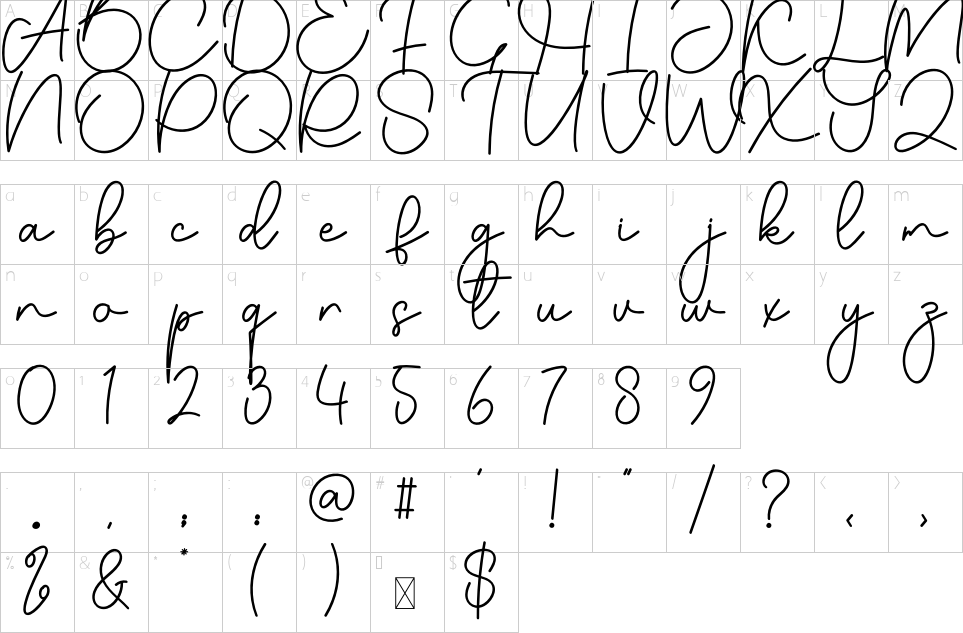
Adelya é uma fonte elegante e moderna, ideal para projetos que exigem sofisticação e simplicidade. Desenvolvida por scratchones, essa fonte foi projetada para se encaixar perfeitamente em qualquer design, seja para fins pessoais ou profissionais. Com seu design minimalista, Adelya oferece uma aparência atraente e fácil de ler. E os benefícios não param por aí, já que foi baixada 423 vezes, isso nos dá uma ideia do seu grande potencial para tornar seu trabalho único e atraente. Adelya é uma fonte perfeita para quem busca algo que seja simples, porém elegante e confiável. Descubra por si mesmo como Adelya pode transformar seus designs em verdadeiros trunfos.